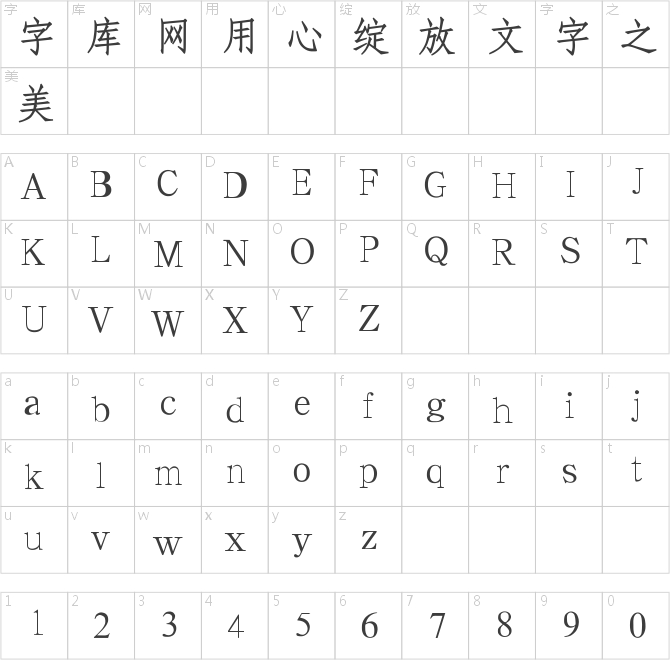
迷你簡(jiǎn)粗仿宋
迷你簡(jiǎn)粗仿宋介紹
迷你簡(jiǎn)粗仿宋字體字庫(kù)是一款讓人賞心悅目、百看不厭的中文字體,適合各類廣告和產(chǎn)品包裝設(shè)計(jì)應(yīng)用,字體大小3.73MB,格式為ttf字體,上傳用戶是 造物設(shè)計(jì)師,作者/版權(quán)方為疑似偽造